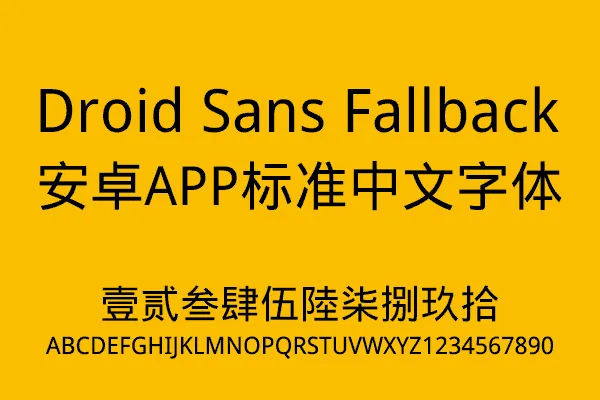
Droid Sans Fallback 是當年 Google 為推出 Android 設備時,委託臺灣華康科技(威鋒數位)為東亞各國字符設計的一款字體,承襲了 DFHeiW5-A 的設計風格,可免費商用。
根據 Ascender 字體公司的介紹,取名 Fallback 是因為 Droid Sans Fallback 是一款作為 Droid Sans 的字集補充而產生的字體,當系統在Droid Sans 找不到需要的字符時會 fallback 到 Droid Sans Fallback上。它採用了字體拼接技術,達到了 5W+ 的字符卻還只有 4.31 MB。
承襲了 DFHeiW5-A 的設計風格,安卓手機默認中文字體。